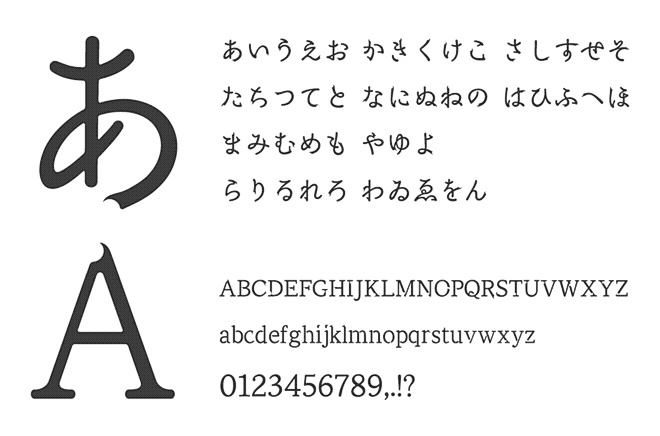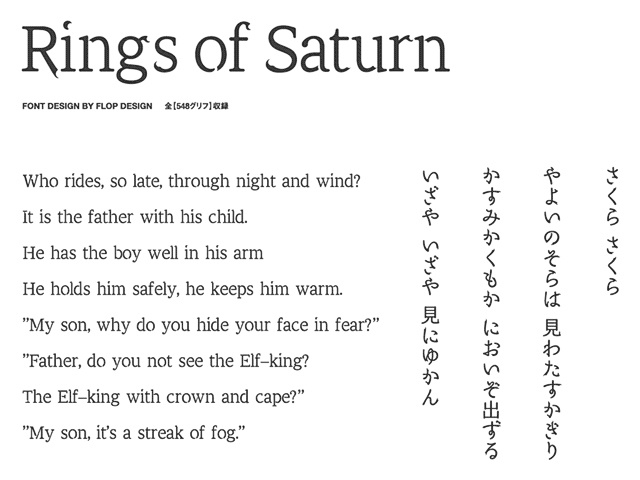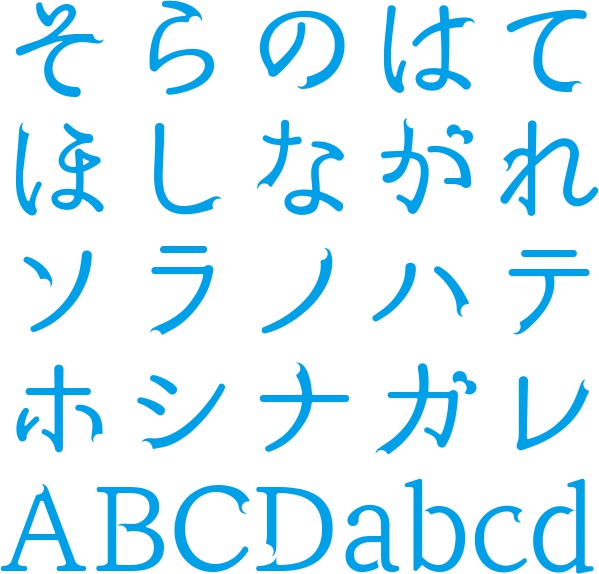
リングス オブ サターン 使いやすそうな、綺麗で色気のあるフォントをというテーマで作りました。先端は正円と、正円をくり抜いた先端と2つが混在してます。陰陽のように、1文字の中でも違った2つの要素が支え合うようなデザインになったらいいなと考えました。 ※フリー版と投げ銭用はいずれも同梱ファイルは同じです。応援よろしくお願いします。 ろんぎぬす様のお誘いで同人誌に初めて参加させて頂きました。嬉しくて自分なりに頑張って誌面に合うようなのを、この本専用に作りました。フリーダウンロード可能ですので、ぜひとも楽しく使ってください。今回は趣味で作成したので、商用利用も可能です。個人利用や同人利用以外でも、ぜひぜひ楽しく使ってください。 フリーフォント使用に当たって フォントをインストールして頂くとパソコンのワープロ、グラフィックソフトなどのアプリケーションを使って自由にデザイン、印刷することができます。個人利用・商用利用にかかわらず、無償で使用することができます。安心して楽しくお使いください。 「SHOTA-E Complex」特設サイト http://0001.miente.design/ ⚠️このフォントは自由に動画に使えるフォントです。ご利用の際は次のクレジットを入れていただけると、ものすご〜く喜びます! –––––––––––––––––––––––––––––– フォント:Rings of saturn フリーダウンロード:https://flopdesign.booth.pm/items/605389 –––––––––––––––––––––––––––––– フォローしてください。 Instagram ▶ https://www.instagram.com/flopdesign.font/ X ▶ https://twitter.com/flopdesign